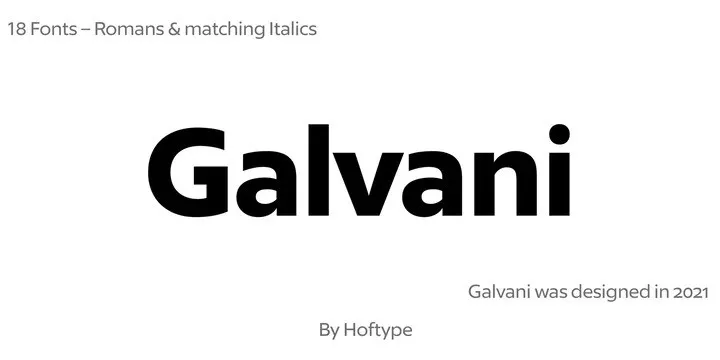
A Galvani Font é uma família de tipo sans-serif com nove pesos variados e nove itálicos, projetada para usos elegantes e de alto nível em qualquer projeto visual. Suas linhas retas e formas retangulares, junto à sua aparência limpa e moderna, mantêm-se fiéis às principais características da design do sans-serif dos últimos anos. Desenvolvida para um público atento aos detalhes gráficos, esta fonte é perfeita para projetos que exigem uma composição minimalista e contemporânea. Com seu design agradável e moderno, a Galvani Font se destaca não apenas como uma opção versátil, mas também como um complemento ideal para qualquer projeto gráfico em busca de elegância e simplicidade no estilo sans-serif.